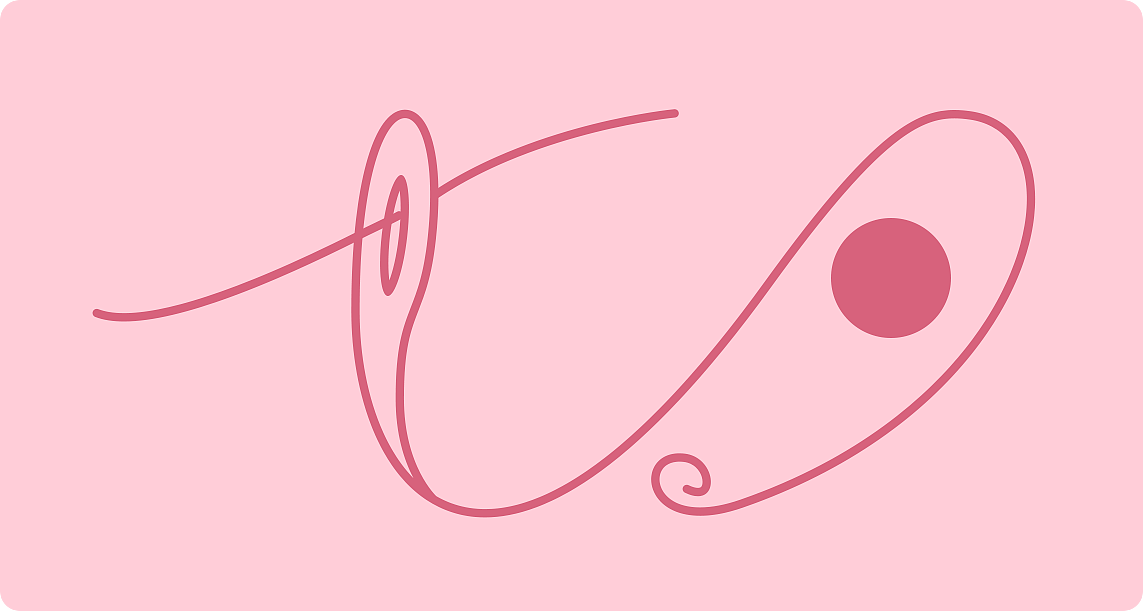
这么多民俗节庆,最爱的就是中秋团圆佳节和七夕乞巧节了,一个是家人之间的暖心团圆,一个是爱人之间凄美又甜蜜的一年一约,金风玉露一相逢,便胜却人间无数,这大概是中国最具浪漫色彩的一个民间节日了。于是,便借着这次民俗艺术的作业,试做了一系列有关民俗仪式的扁平化极简线性图标设计。
七夕的字体Logo设计:灵感来源与七夕之夜,民间的穿针乞巧,将穿针乞巧和七夕二字结合,让人能更好的理解七夕的民俗涵义。
织女的图形设计
牛郎的图形设计
穿针乞巧
喜蛛应巧
为牛庆生
吃巧果